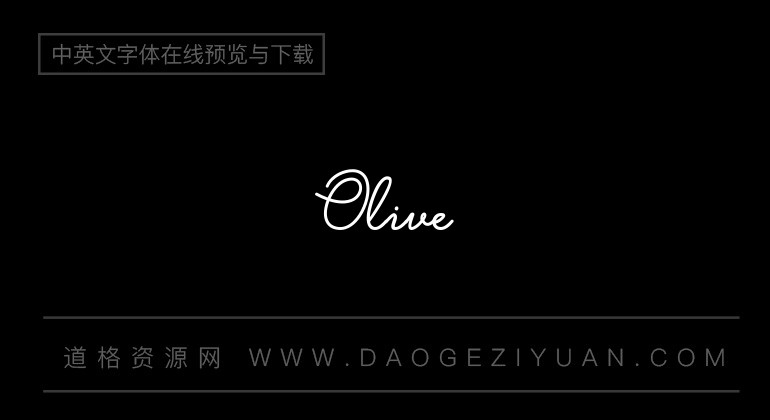
Olive 字体是一款由 Alex Haigh 创作的极具现代感的字体,它采用简洁的线条,拥有清晰的视觉效果,是一款极具设计感的字体,适合用于各种现代化的设计项目中。Olive 字体拥有很好的可读性,同时还具有灵活的字重,可以满足不同的设计需求。此外,Olive 字体还具有极具特色的折叠字母,可以给设计师带来更多创意灵感。内容介绍
Olive是一款非常不错的手写艺术字体,具有很好的视觉感,适合于文化类的宣传设计、商业类品牌的广告和产品包装设计以及个性化文字排版等较多场景。